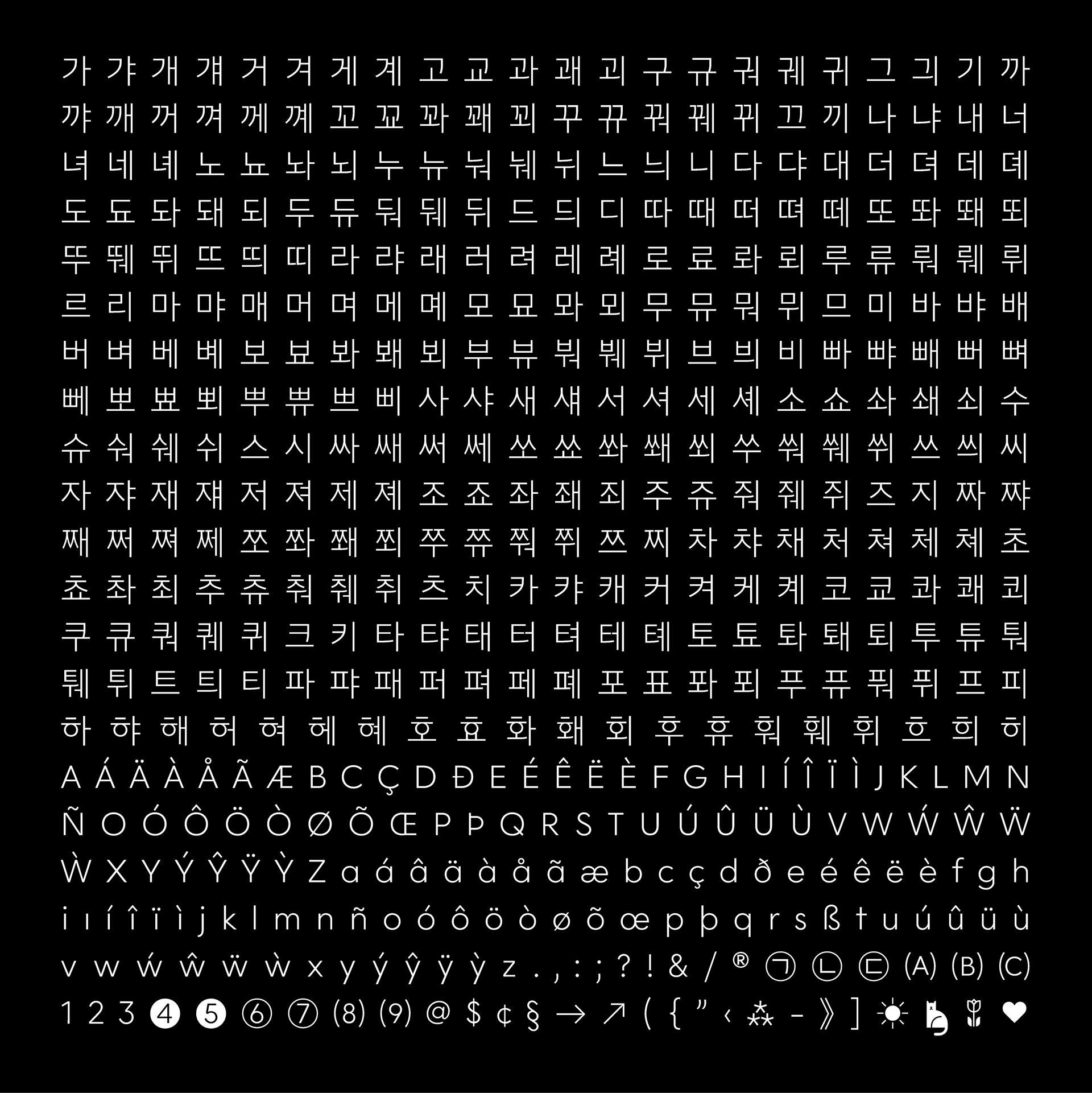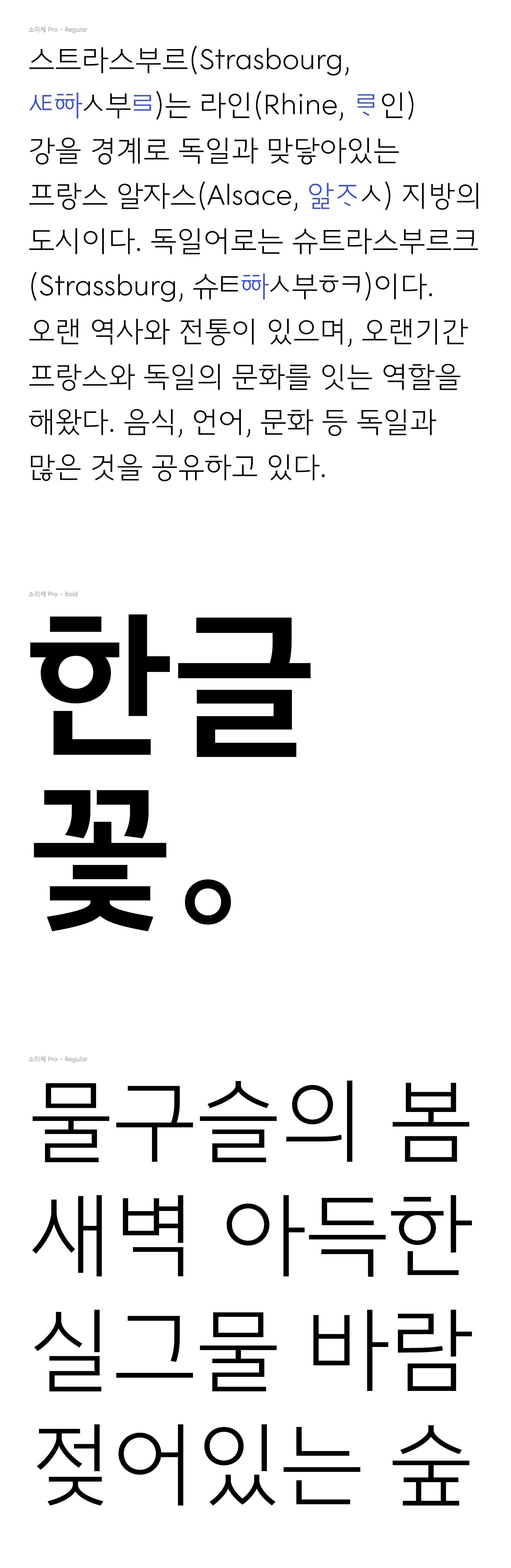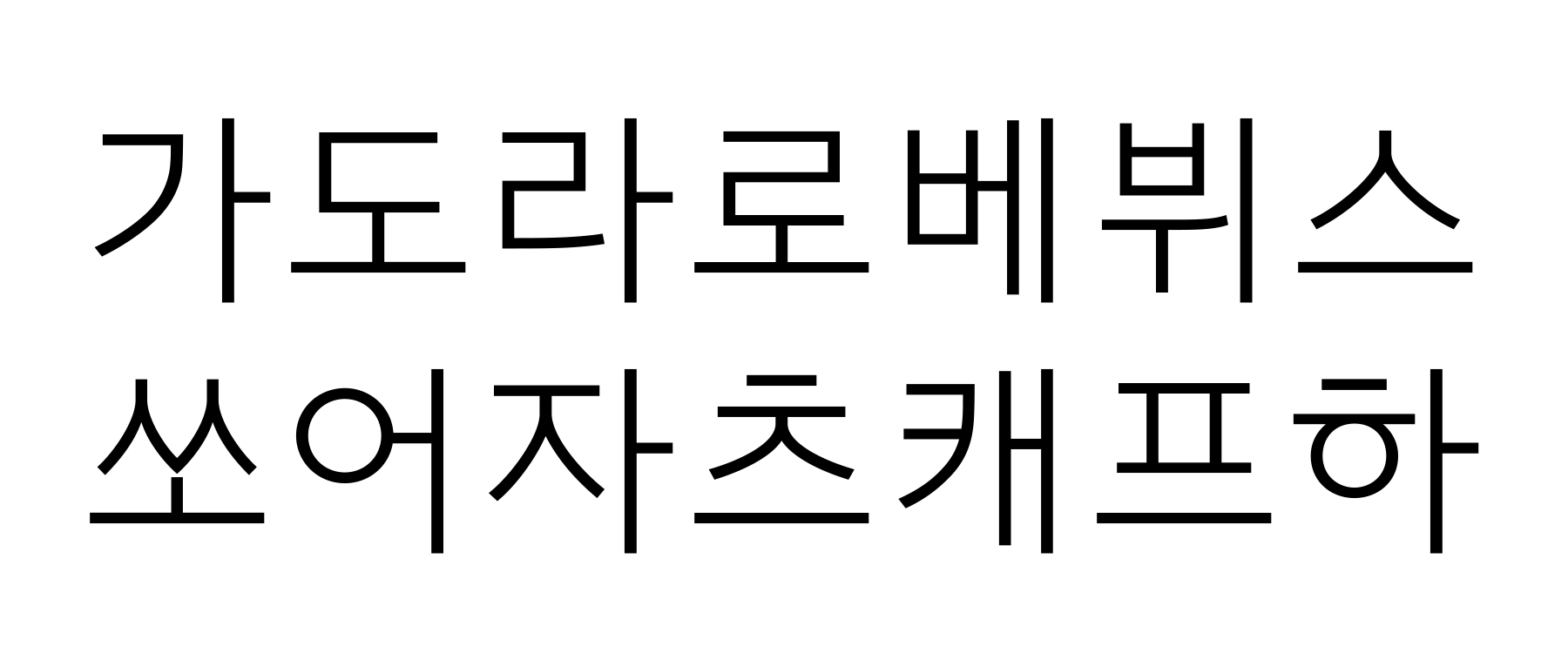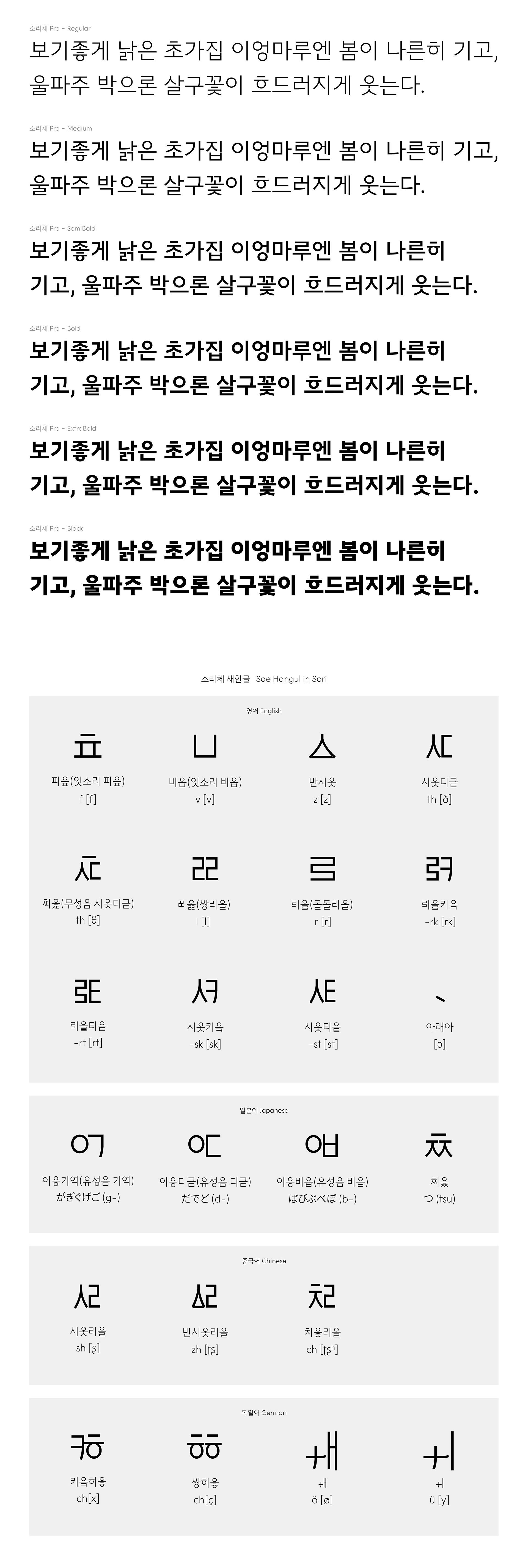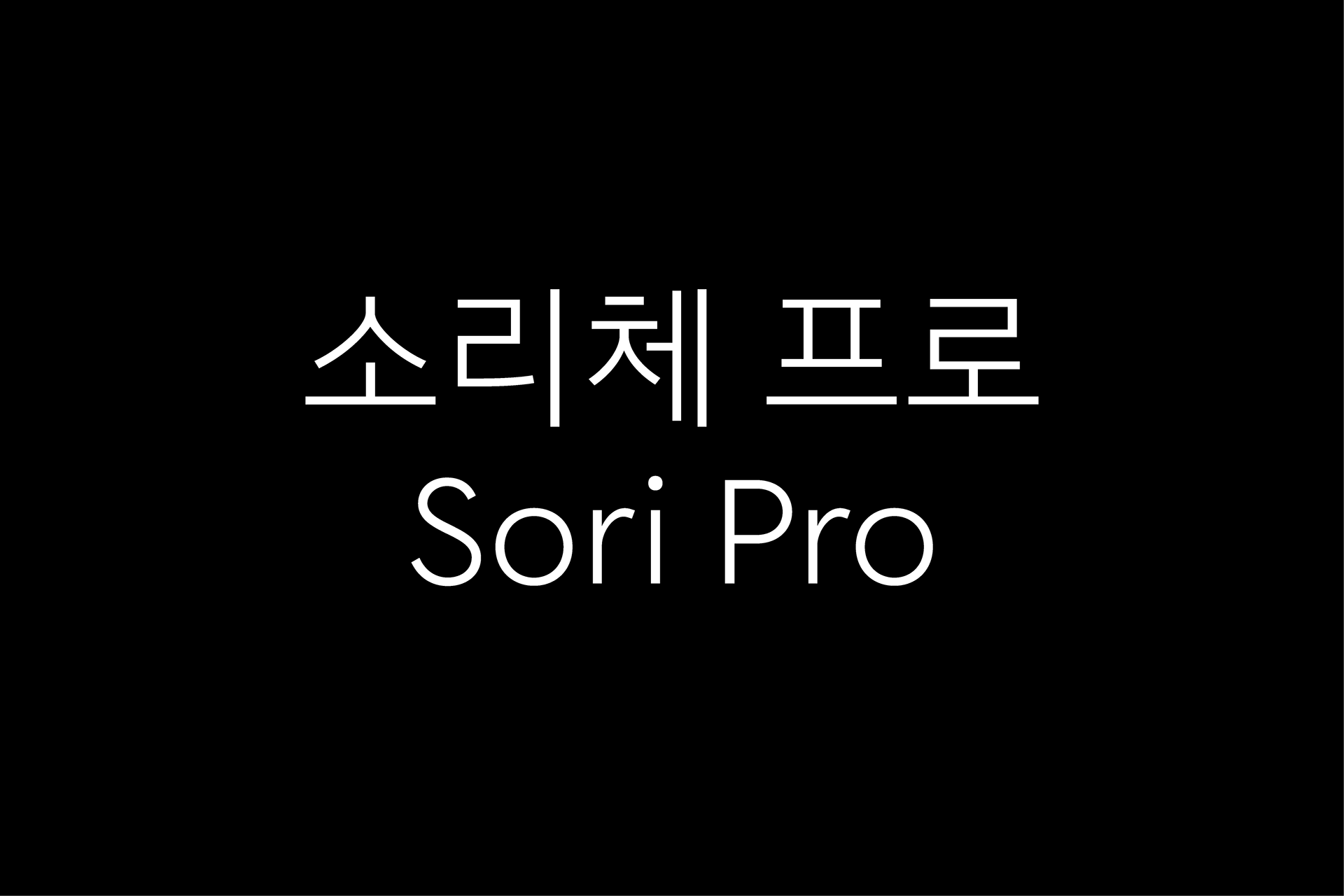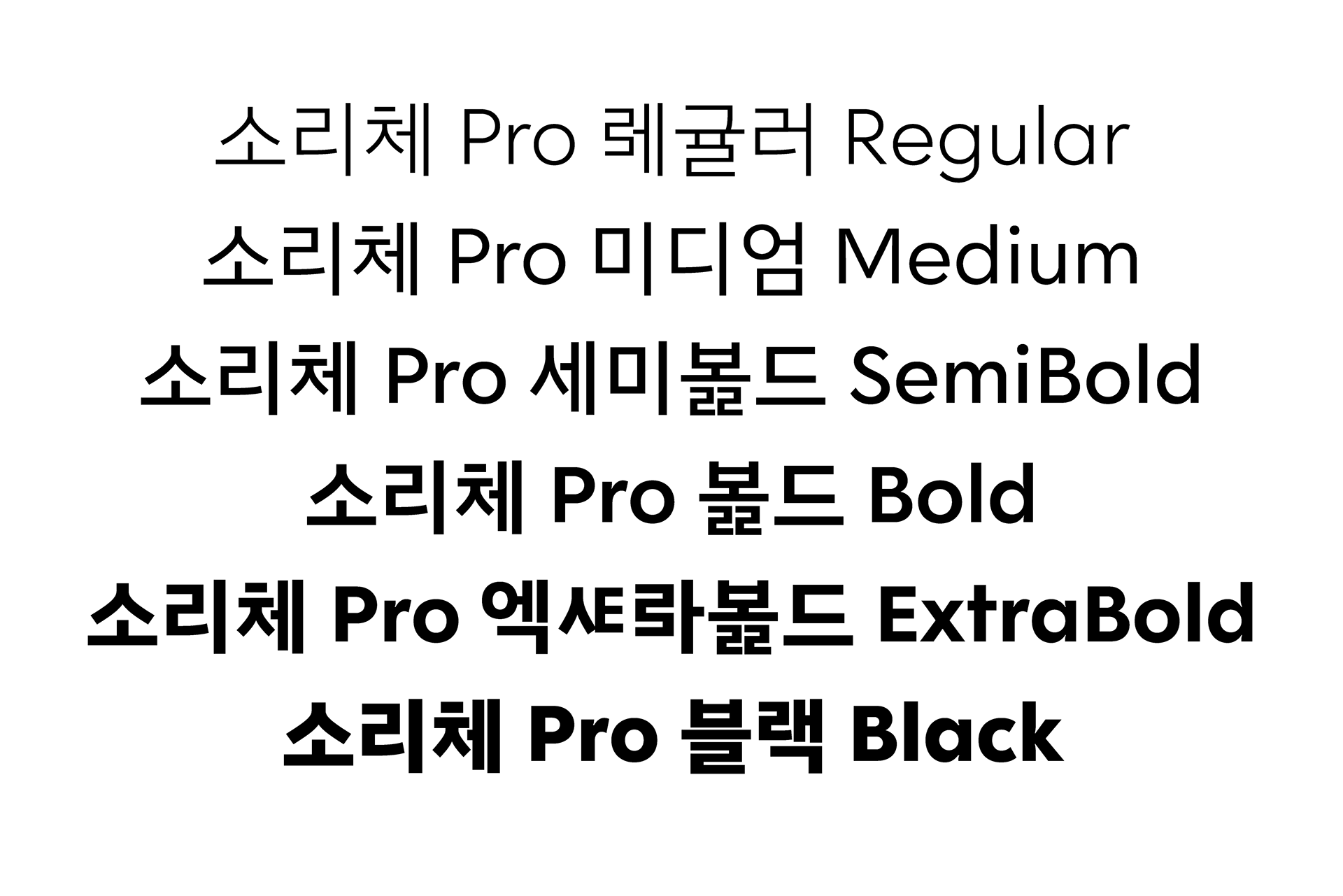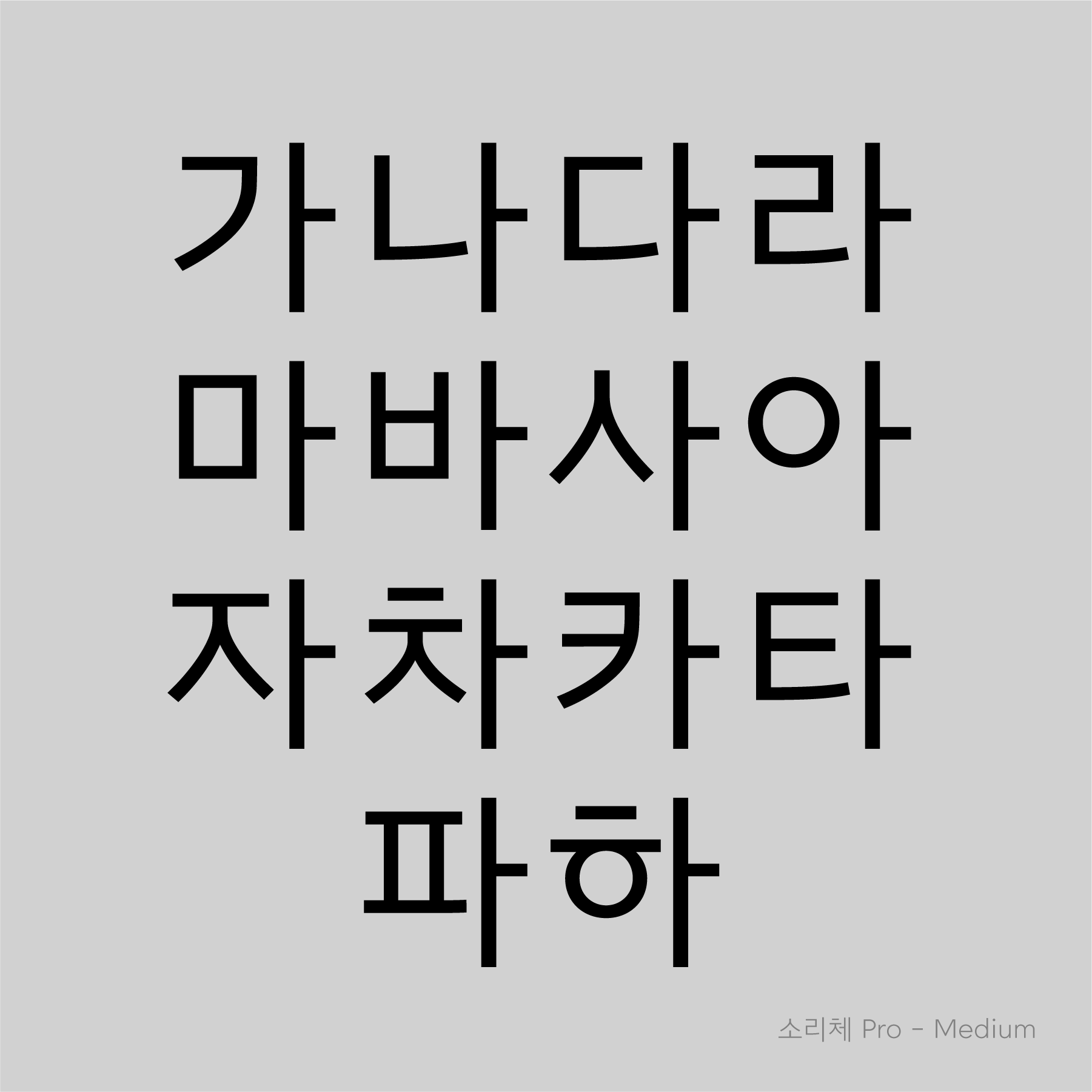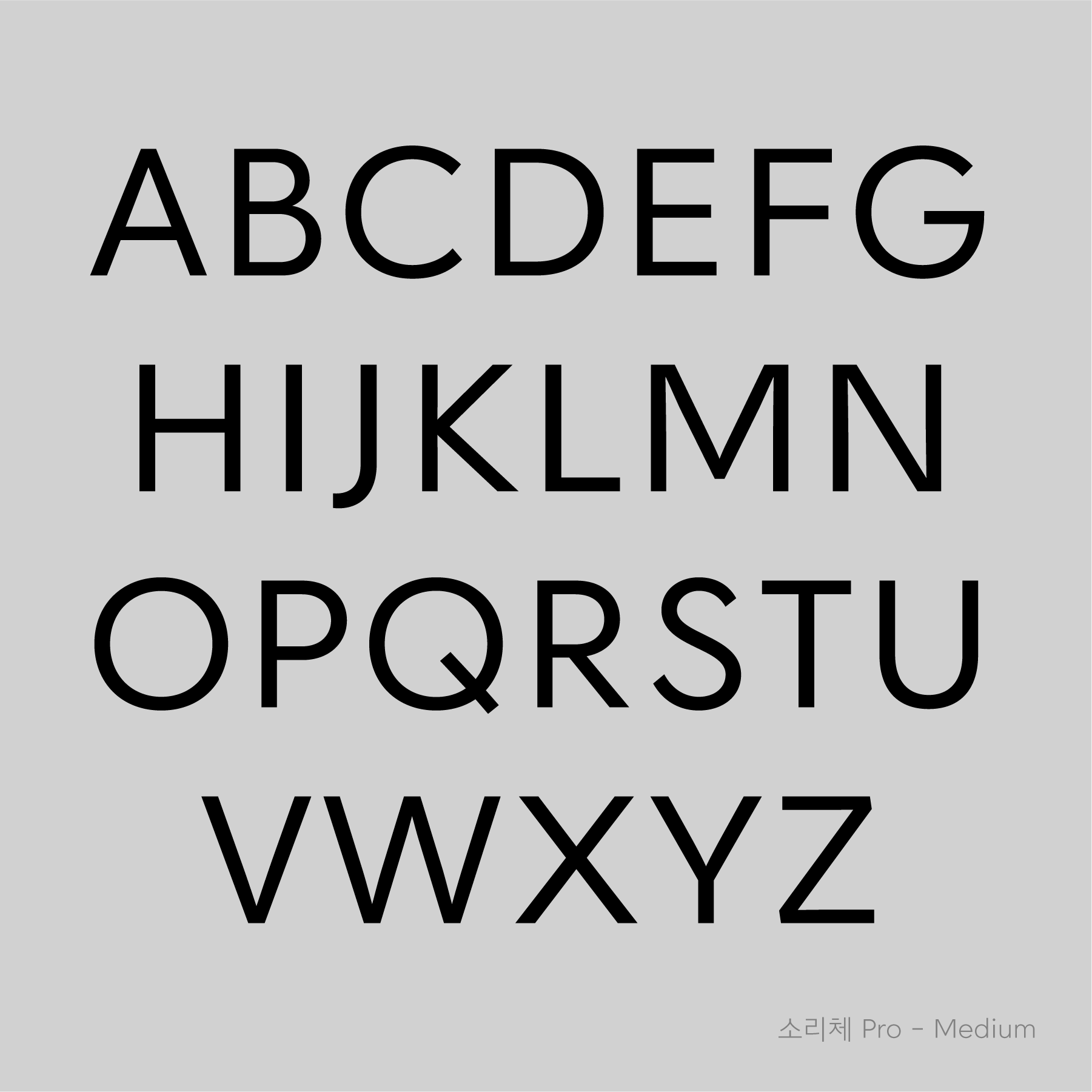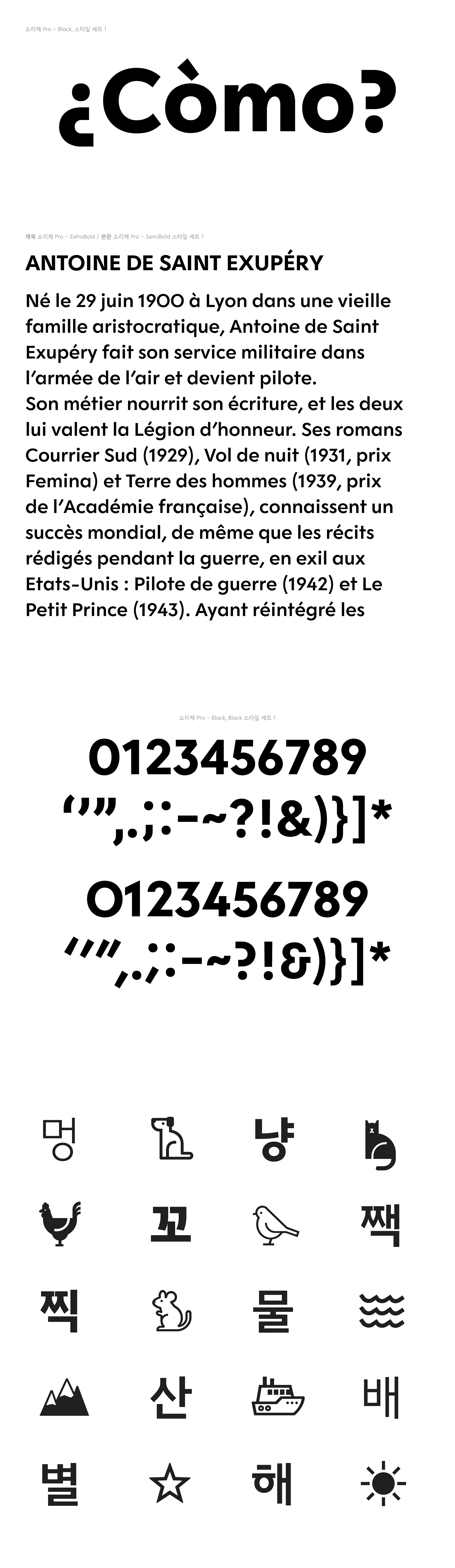
소리체
Sori
우리말에 없는 외국어의 소리를 표현하기 위한 새로운 한글 디자인 프로젝트
A new Hangul design project for phonetic transcription of foreign languages absent in Korean
«소리체»는 우리말에 없는 외국어의 소리를 표현하기 위한 새로운 한글 즉, ‘새한글(Sae Hangul)’이 포함된 글꼴이다. 훈민정음의 ‘가획, 합자’와 같은 제자 원리에 따라 ‘f l r v z’ 등과 같이 낯선 외국어 소리를 위해 새로운 자모를 디자인했으며, 일부는 사라진 옛한글 ‘반시옷(ㅿ)’,  ‘아래아(ㆍ)’ 의 형태를 되살렸다.
«소리체» 글꼴 디자인은 훈민정음 창제 당시 ‘정음체’의 영향을 받아 수평, 수직, 정원, 사선으로 구성된 기하학적인 표정을 지니는 동시에, 본문용으로 써도 손색이 없도록 유연하게 시각보정했다.
«소리체»라는 이름은 훈민정음 정인지 서문의 “천지자연의 ‘소리’가 있다면 반드시 천지자연의 ‘글자’가 있다”라는 문구에서 영감을 받아 지었다. 첫 스케치는 노은유의 2005년 홍익대학교 졸업 전시 프로젝트에서 시작했으며, 이어서 석사 논문 주제로서 연구를 지속하여 ‘일본어 음성 표기를 위한 한글 표기 체제 연구(2008)’를 발표했다. 그 후 새로운 한글 자모를 폰트로 구현하는 기술적 문제로 오랫동안 묵혀두었다가 2020년에 이주희 디자이너가 노타입에 합류, 소리체 개발에 함께 참여하여 정식 폰트로 출시했다. 2021년 소리체는 6개 굵기의 Pro 버전으로 확장되었다.
«Sori» is a typeface that includes ‘Sae-Hangul’ (New Hangul), designed to express foreign sounds not native to the Korean language. Following the principles of Hunminjeongeum—such as Gahoek (adding strokes) and Habja (combining characters)—new letters were created for unfamiliar sounds like ‘f, l, r, v, z’. It also revives the forms of obsolete letters (Yet-Hangul) like Bansiot (ㅿ) and Arae-a (ㆍ).
Influenced by the early ‘Jeongeum’ style, the letterforms feature a geometric expression composed of horizontal, vertical, diagonal lines, and perfect circles, while fluidly optically corrected for body text.
The name «Sori» (sound) comes from Jeong In-ji's preface to Hunminjeongeum: “If there is a sound of heaven and earth, there must be a character of heaven and earth.” The initial sketches began as Eunyou Noh’s 2005 graduation project at Hongik University, leading to her 2008 master's thesis, A Study on the Hangul phonetic alphabet system for phonetic transcription of Japanese. Shelved for years due to technical challenges in font implementation, the project was resumed in 2020 when designer Joohee Lee joined NohType, leading to its official release. In 2021, «Sori» was expanded into the Pro version with six weights.